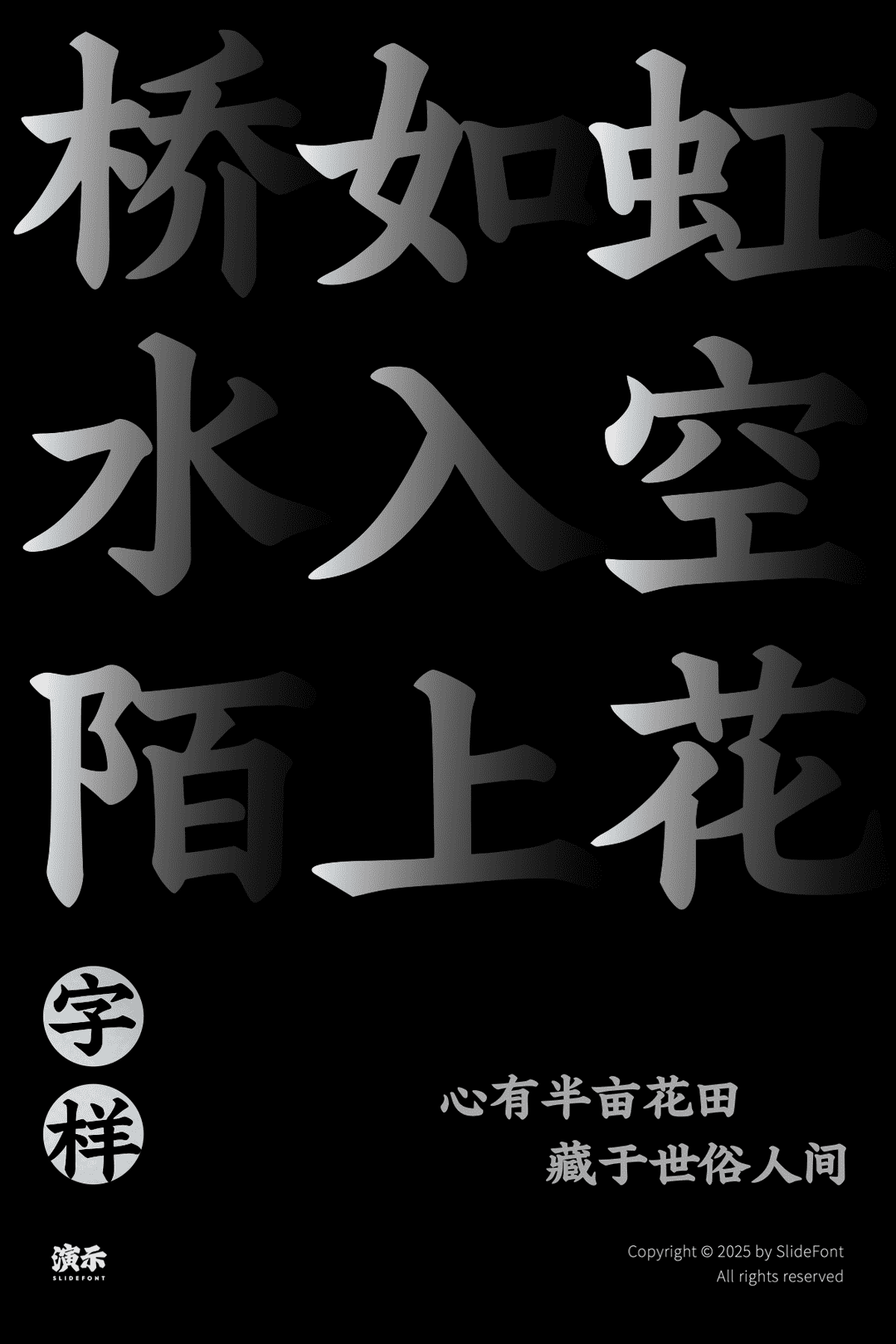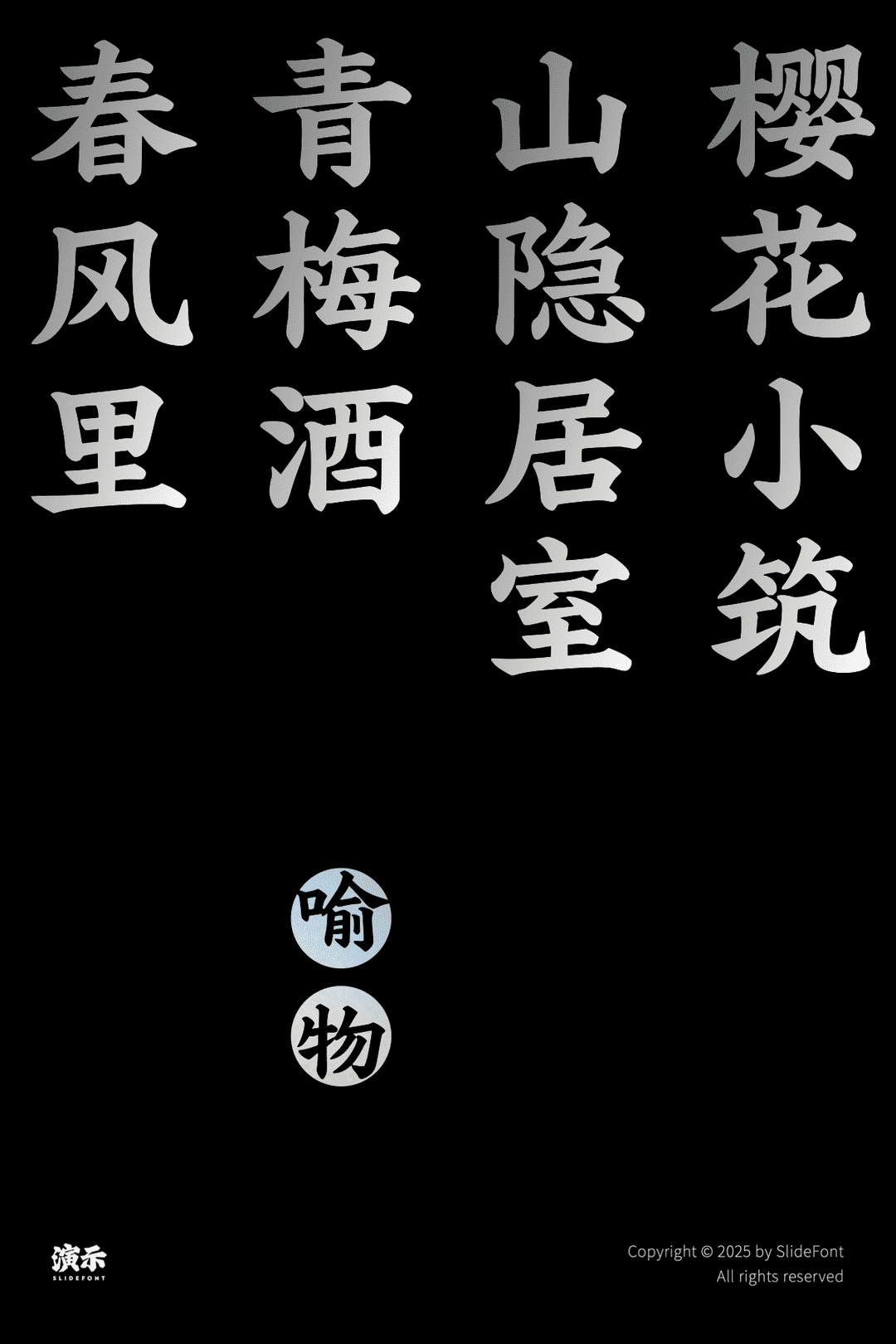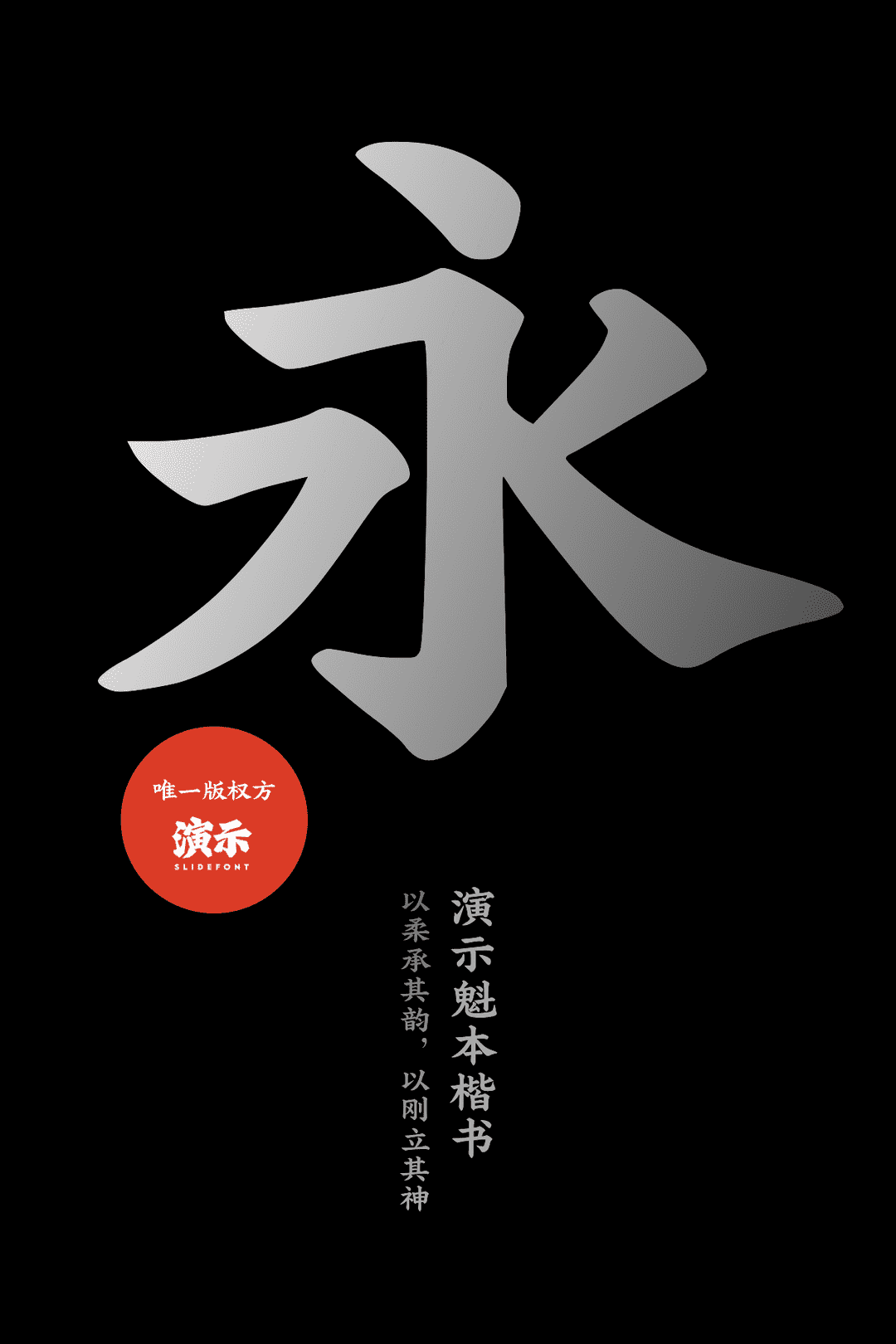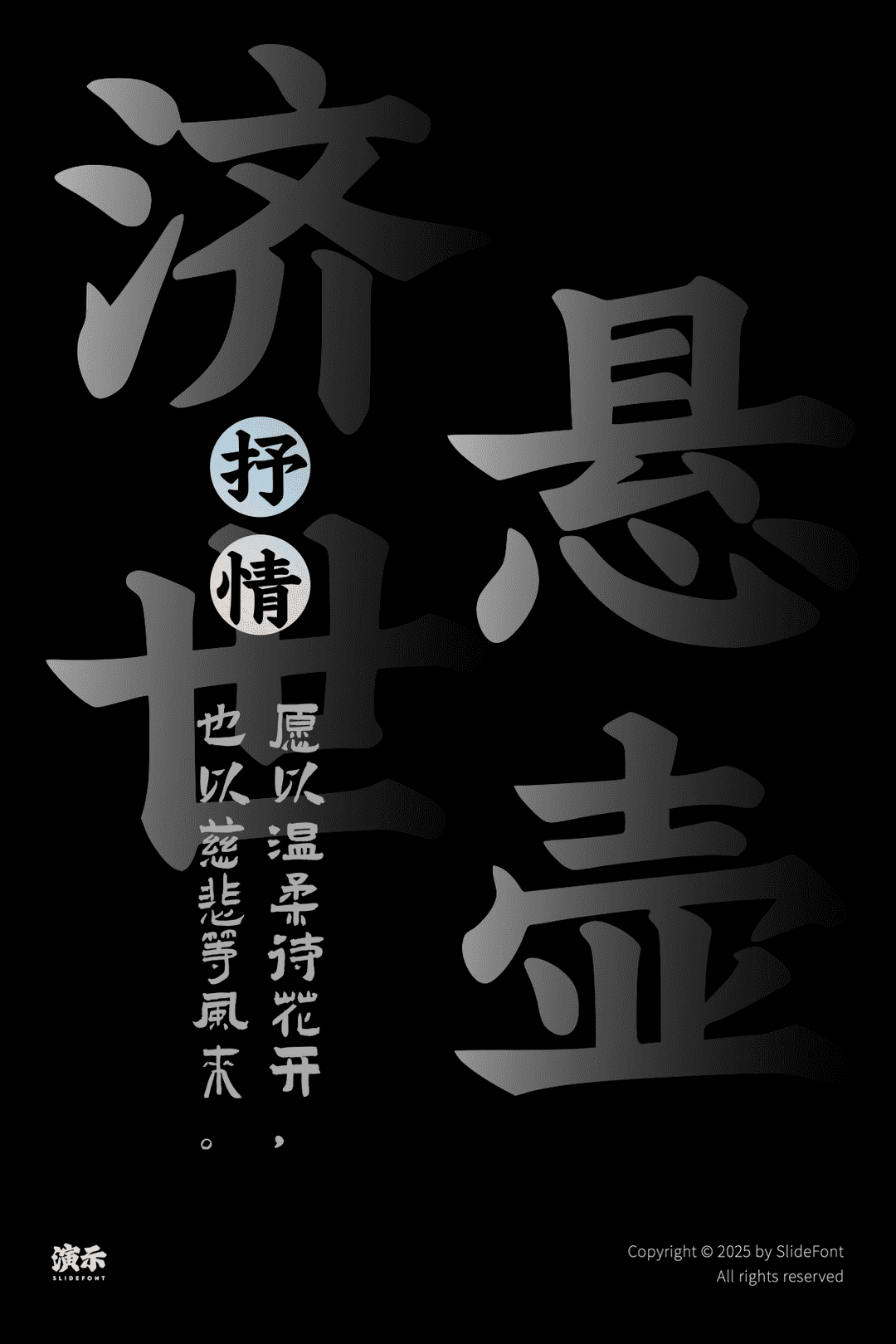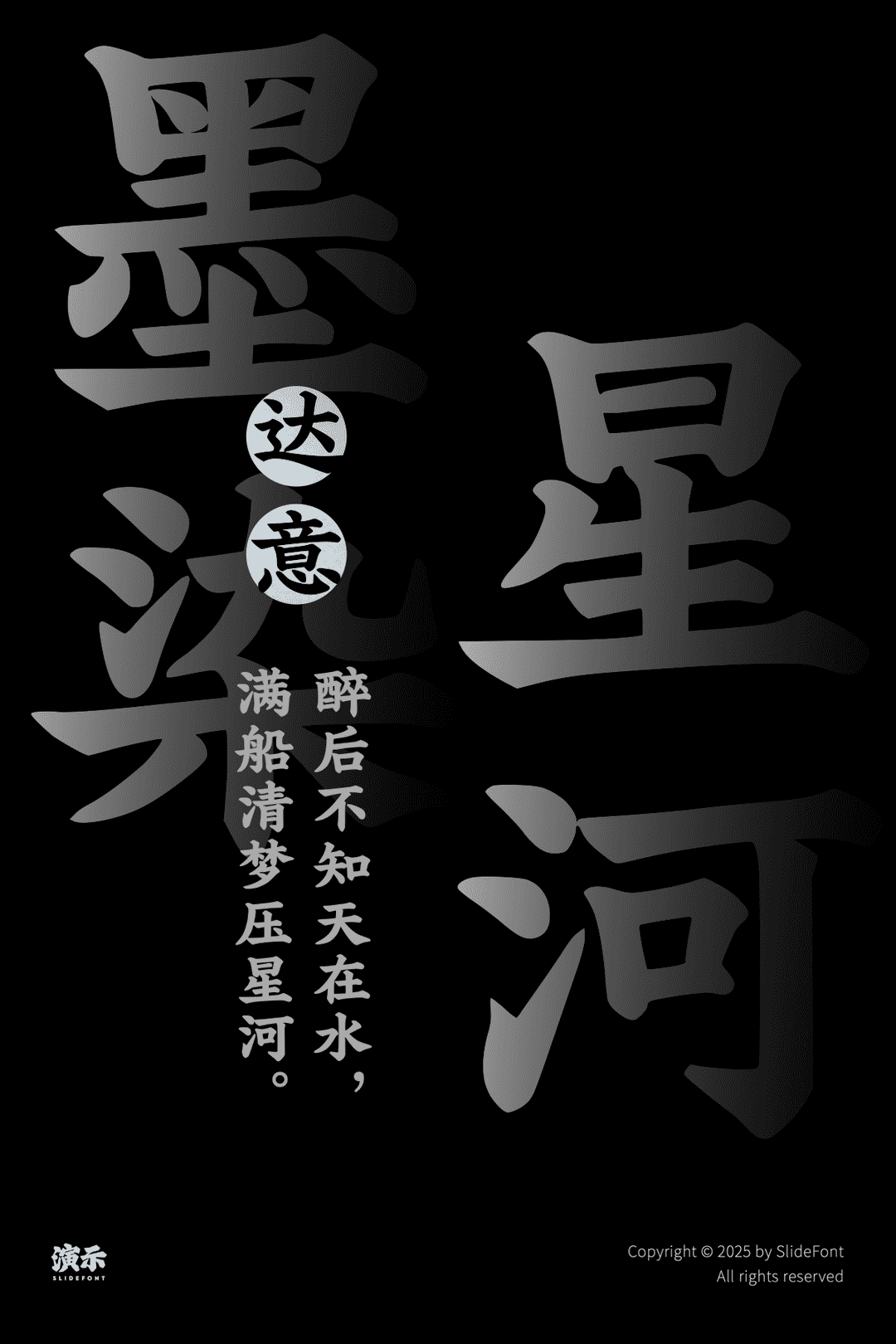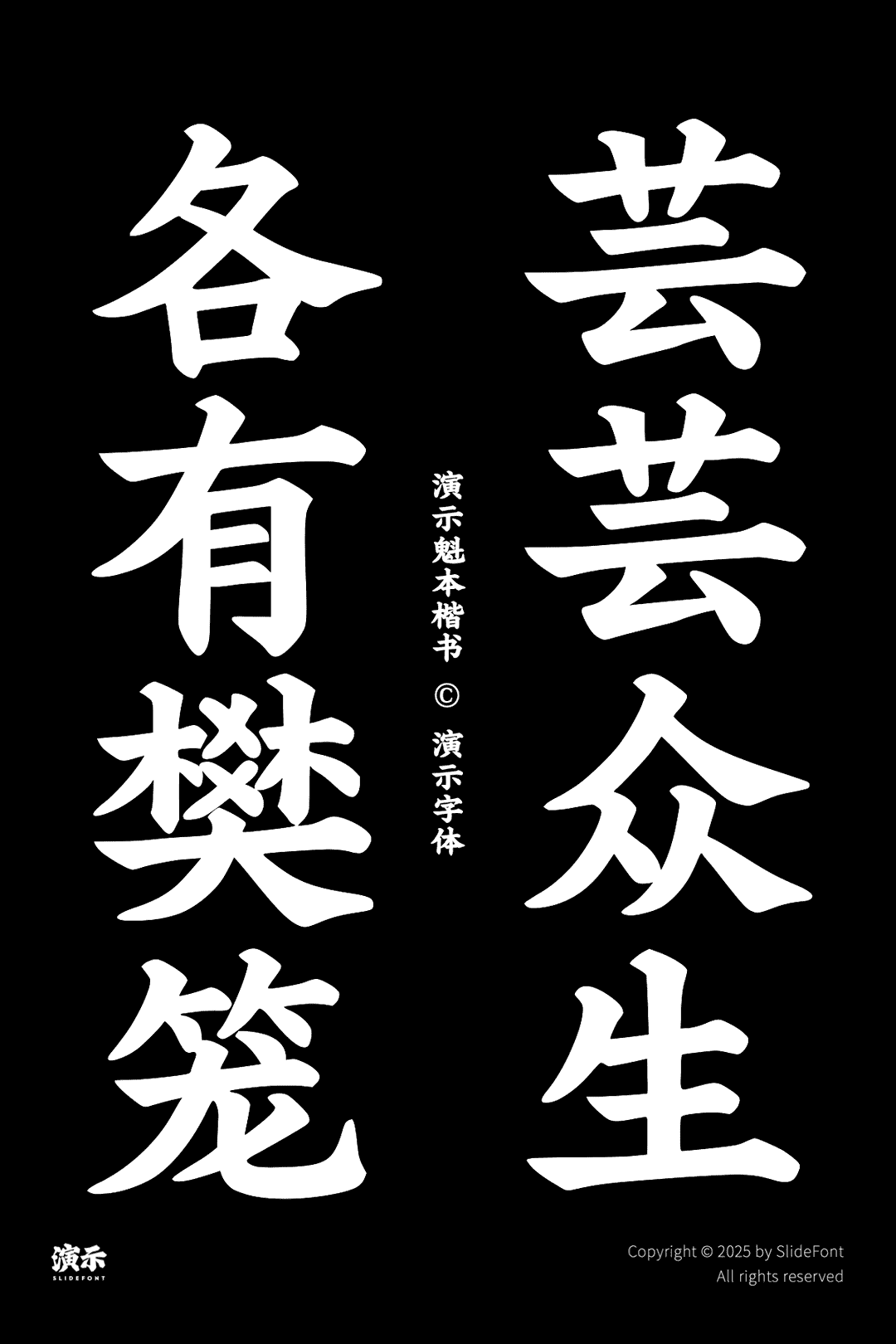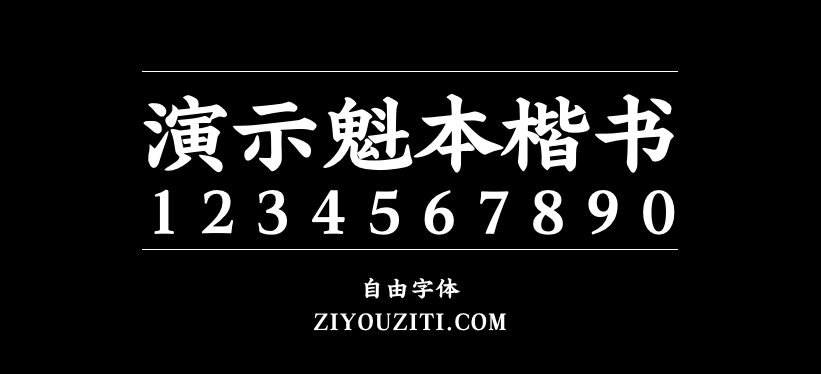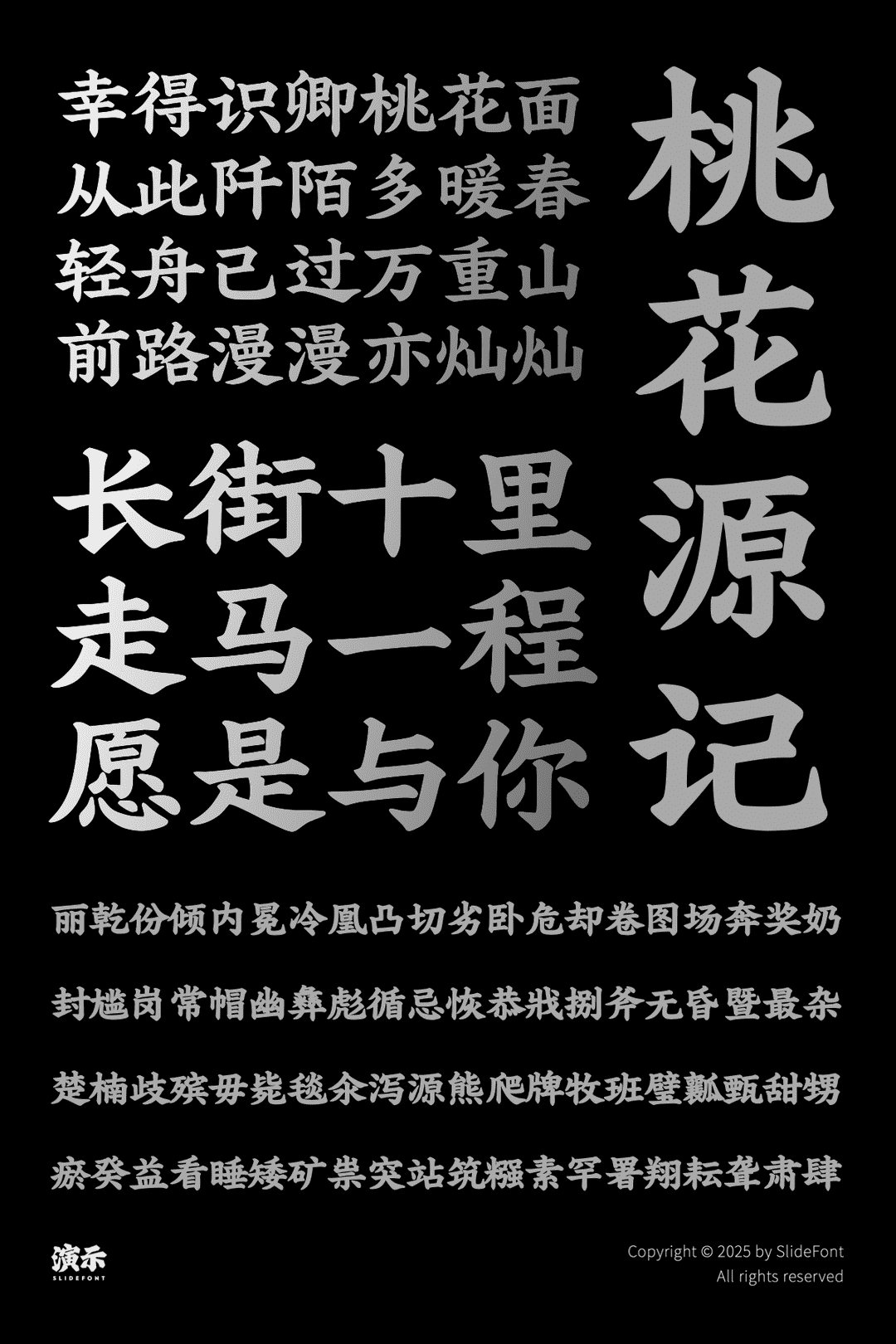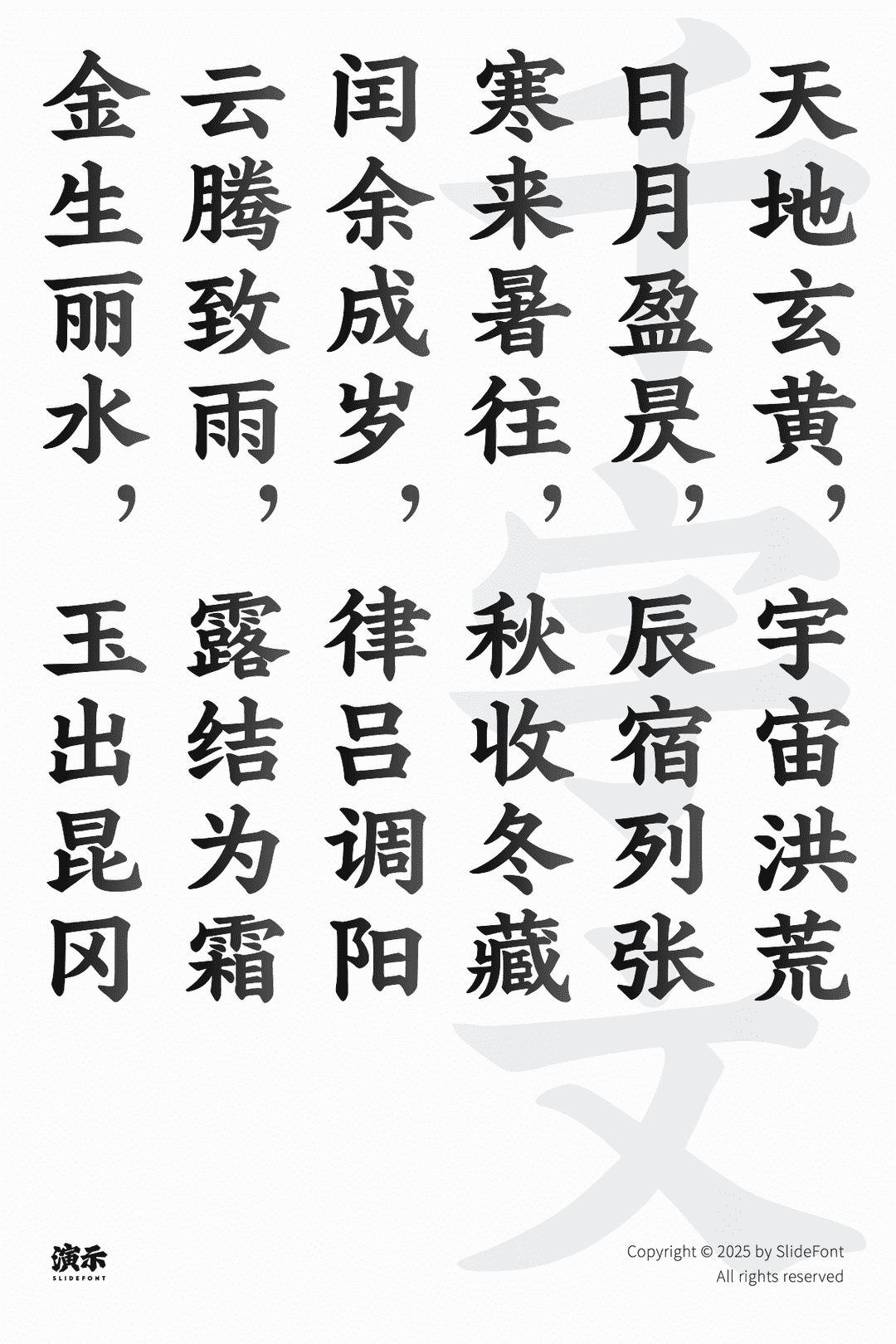
- 字体作者keynote研究所
演示魁本楷书
演示魁本楷书是演示字体(keynote研究所)发布的第6款免费商用字体,前面5款分别是:演示秋鸿楷、演示夏行楷、演示春风楷、演示悠然小楷、演示佛系体
演示魁本楷书开发于2025年夏季,汲古《魁本大字五经》创作的美术字。GB2312-80,字符总数8434。